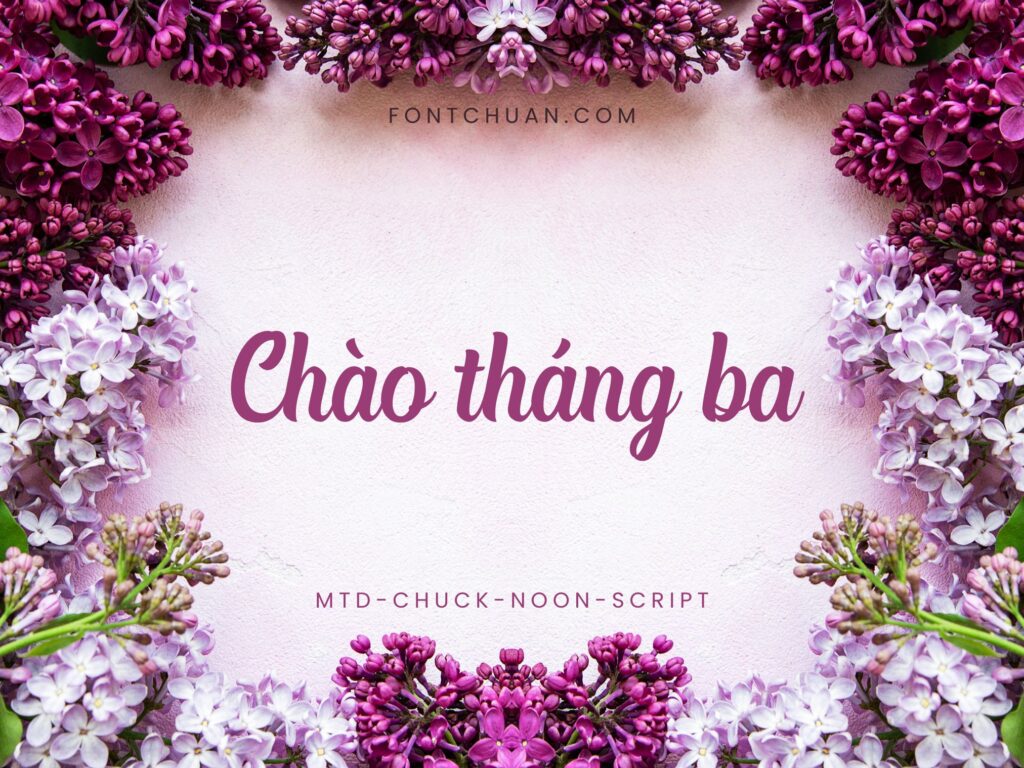
Font MTD Chuck Noon Script Việt Hóa
Font MTD Chuck Noon Script là một kiểu chữ viết tay đậm nét, được thiết kế bởi Twicolabs Fontdation và đã được Việt hóa bởi Mộc Hạ. Font này hỗ trợ đầy đủ tiếng Việt cùng hơn 90 ngôn ngữ khác, mở rộng khả năng ứng dụng trong các thiết kế đa ngôn ngữ. Đây là một trong những phông chữ được cộng đồng thiết kế đánh giá cao và sử dụng trong nhiều dự án sáng tạo, đáp ứng nhu cầu đa dạng của người dùng.
MTD Chuck Noon Script nổi bật với các đường nét mạnh mẽ và tự nhiên, tạo cảm giác năng động và hiện đại. Font rất phù hợp cho các thiết kế logo, tiêu đề, bao bì sản phẩm, thiệp mời và các ấn phẩm đòi hỏi sự sáng tạo và nổi bật. Các ngành nghề phù hợp bao gồm quảng cáo, giáo dục và công nghệ. Font này cũng lý tưởng cho các sự kiện như Tết, Giáng sinh, Valentine và các lễ hội khác.